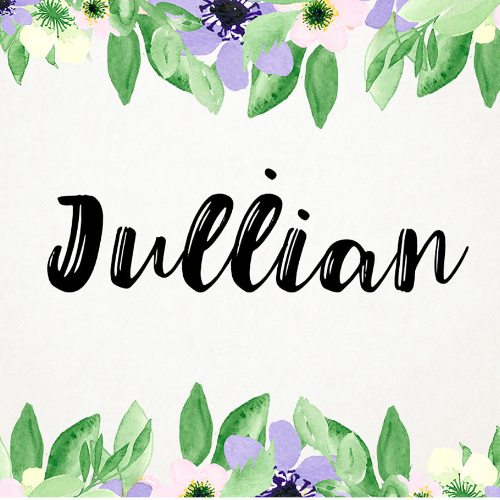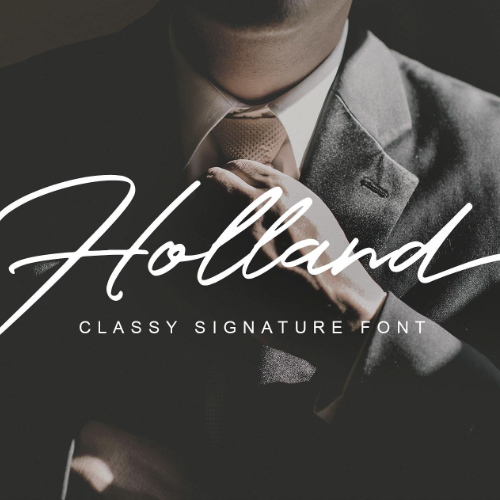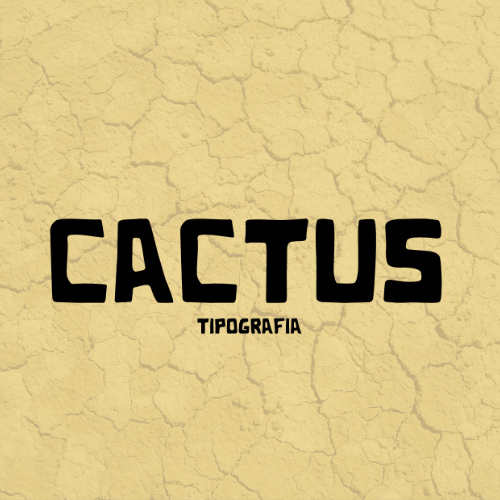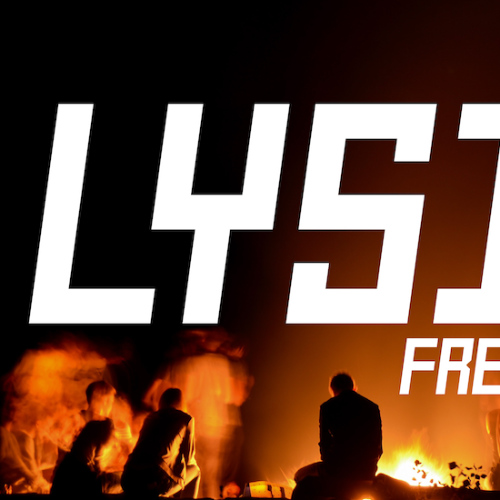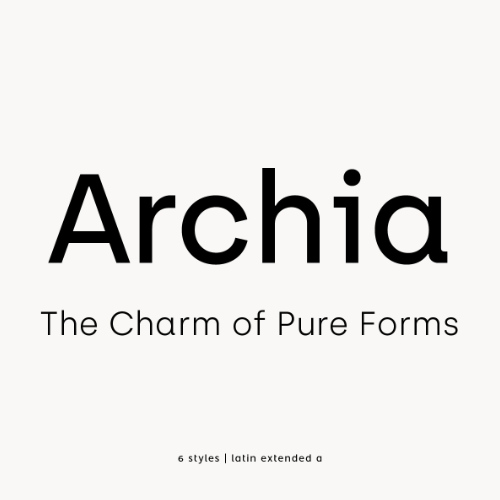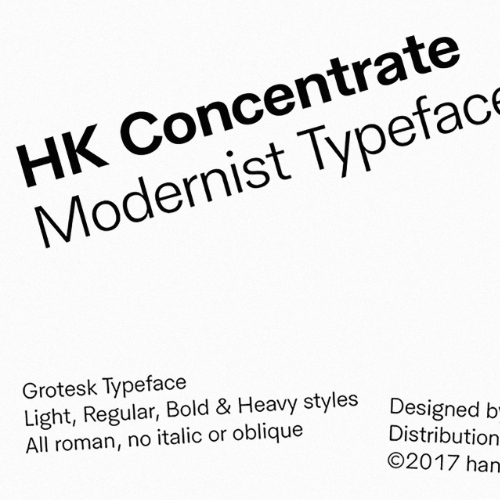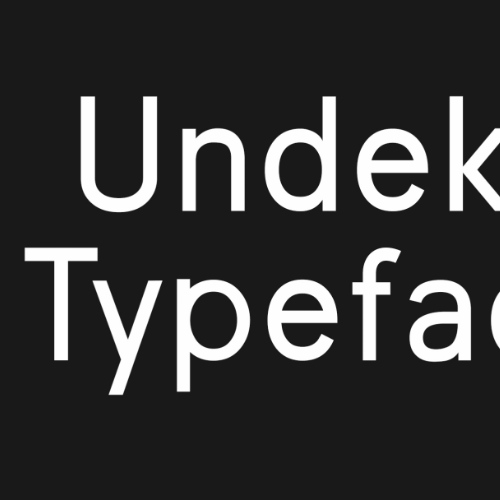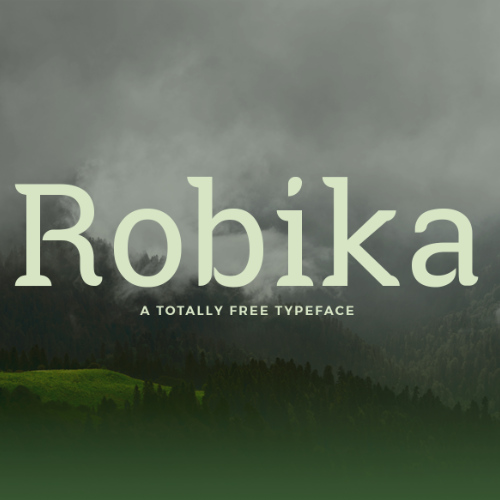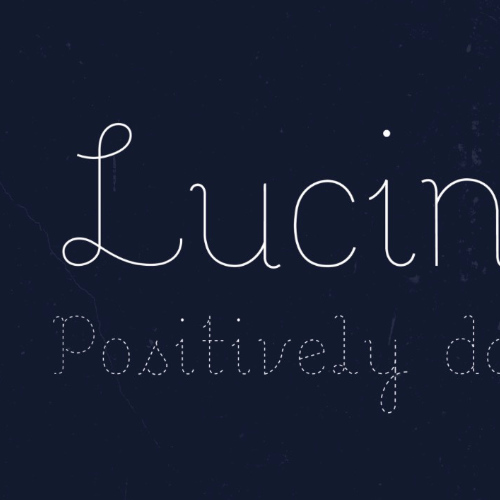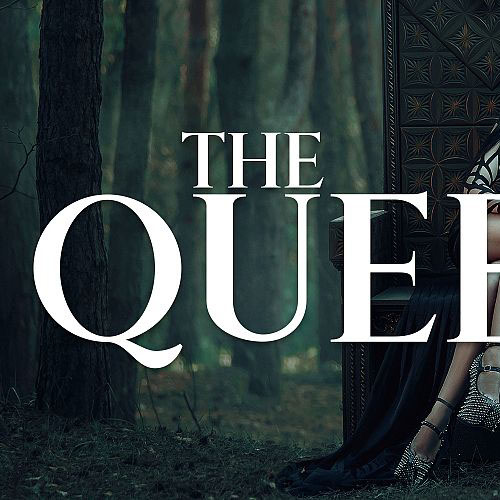
10 Typographies gratuites à télécharger
Comme chaque mois, Graphiste.com vous propose une sélection de 10 plus belles typographies qui ont fait leur apparition sur le net. Ces polices d’écriture sont bien évidement à téléchargement gratuitement. Et comme toujours, il y en a pour tous les goûts : Serif, Sans Serif, Handwriting…
Julian – Free Font
Cactus – Free Font
Lysis – Free Font
Archia – Free Font
HK Concentrate – Free Font
Undeka – Free Font
Robika – Free Font
Lucinda – Free Font
The Queen – Free Font
Holland – Free Font